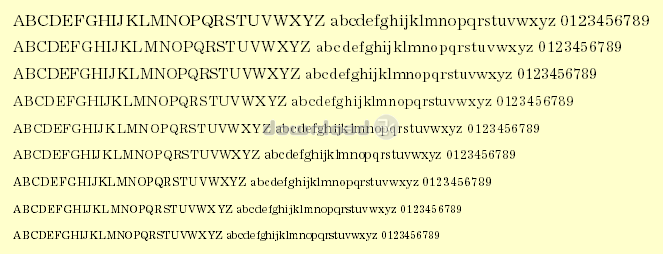
"Serif newspaper font, legible on newsprint"
Rubicon Fuentes de Essex. Posdata. Serif periódico, legible en papel de periódico. Como Excelsior. Para el cuerpo del texto en periódicos, boletines, etc Recomendado tamaño de 8,5 puntos. Precisa y dio a entender, haciendo coincidir las métricas de fuente, juego de caracteres estándar, kerning pares. La calidad profesional de impresión de inyección de tinta, láser, cajista a 3500 dpi. Contiene una fuente de prueba, envíe $ 12 para recibir todas las 3 fuentes de producción.Requisitos: Older versions of Mac OS require Adobe Type Manager.